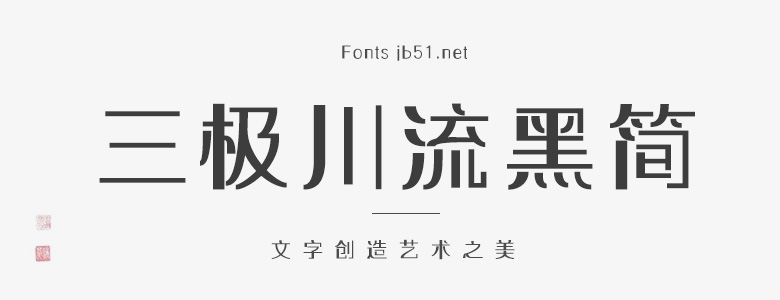
三極川流黑簡字體整體風格鮮明,筆畫平直、錯落有致。字形以橫起筆,縱向變化,筆畫由粗細相間的圓弧連接,如川流不息的河水。它的靈感來源于河流,給人一種川流不息,時起時落的感覺,具有連綿不絕的氣質(zhì)。視覺效果簡潔易識別,實用性強。本作品適用于廣告標題與時尚雜志、各類屏幕顯示及影視字幕等。歡迎喜歡三極川流黑簡字體的朋友前來下載使用。